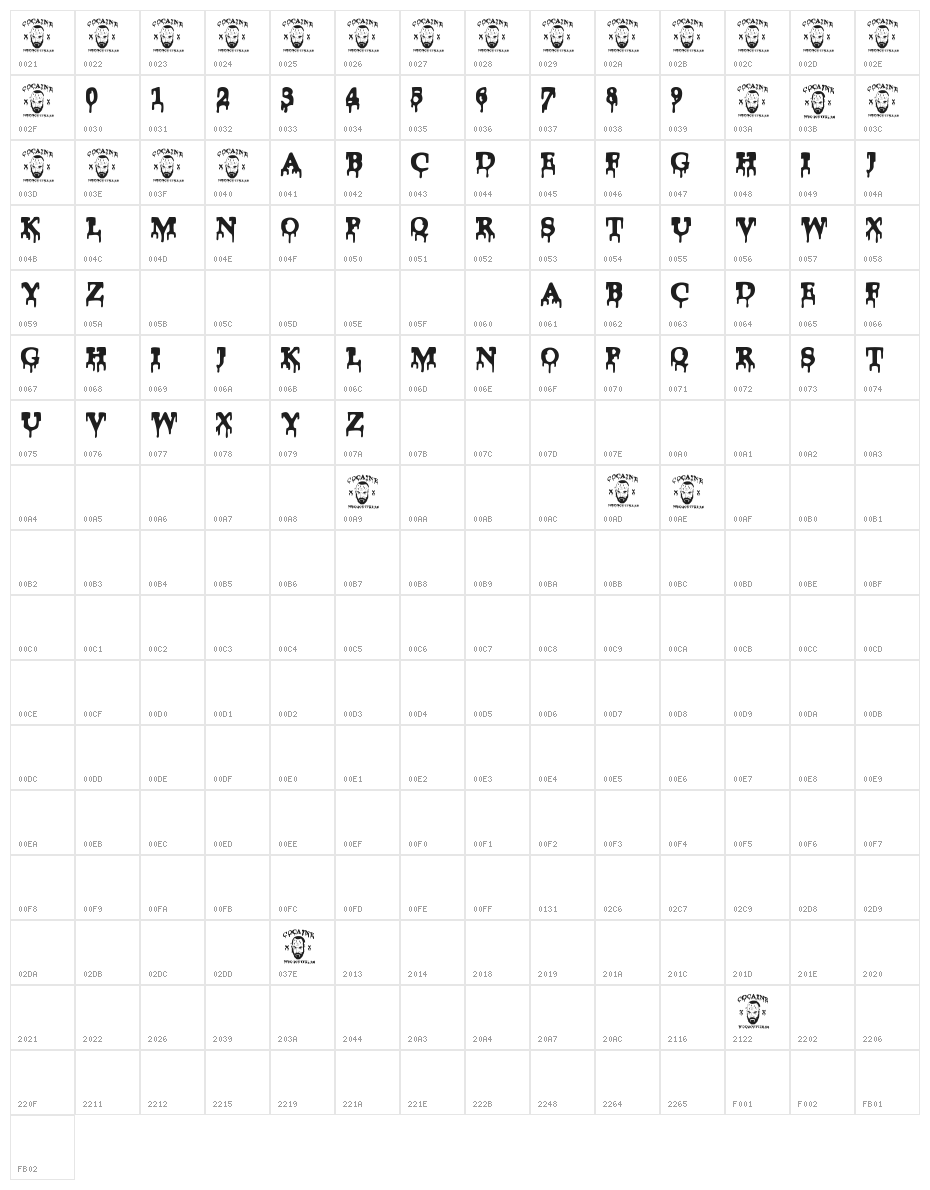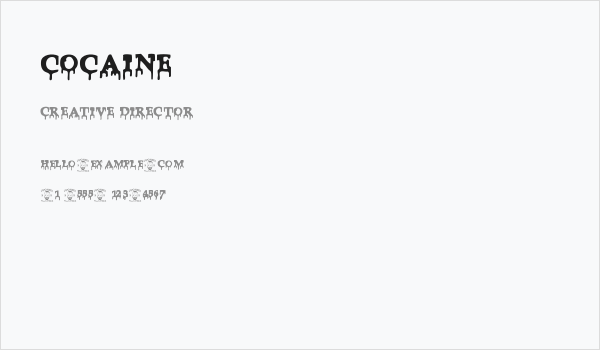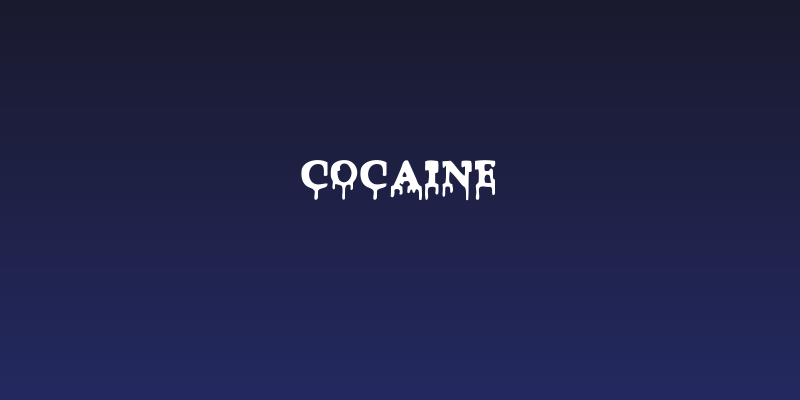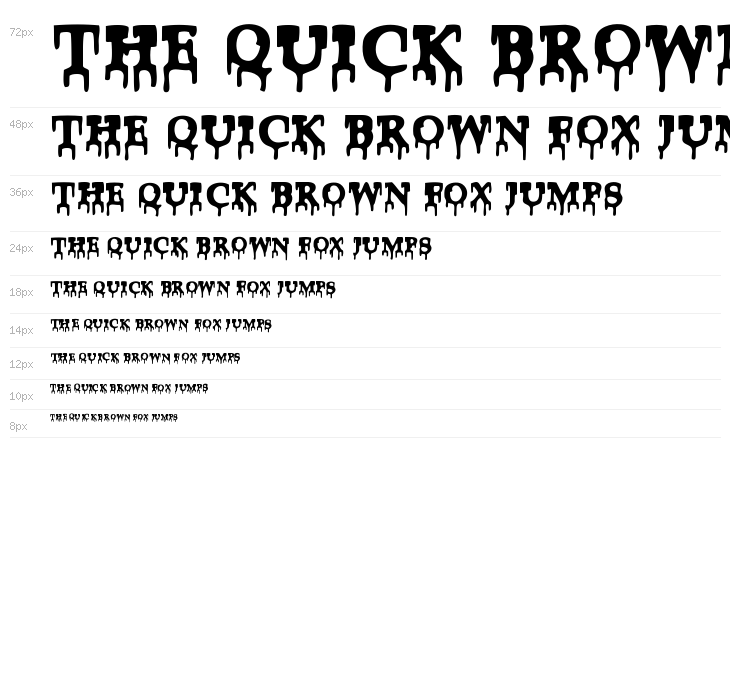
Cocaine Font
✎ Horror
| Progetti proposti | Ideal for Halloween-themed designs, horror movie posters, edgy branding, or any project requiring a dramatic and eye-catching font. |